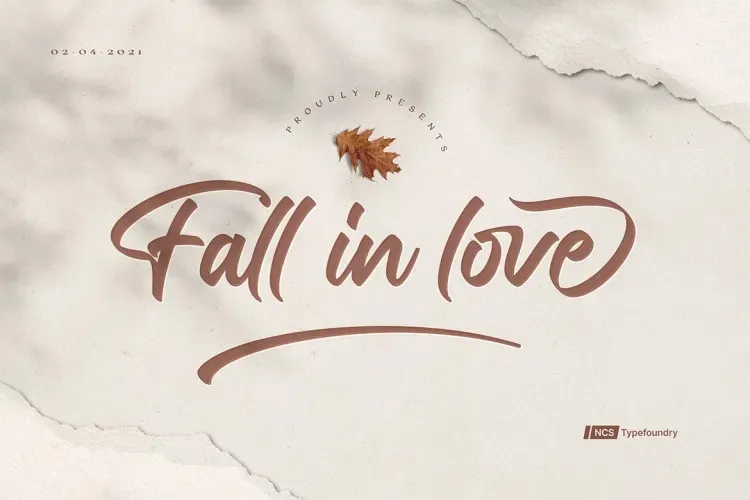
Fall in love Script Font – Download Grátis
A fonte “Fall in Love Script Font” é uma elegante tipografia feita para quem busca um toque delicado e criativo na hora de criar trabalhos artísticos e conceituais. Inspirada no estilo dos traços suaves de desenho a mão, esta fonte foi projetada com detalhes robustos em suas linhas e bordas arredondadas levemente onduladas. Perfeita para aplicar em logotipos, roupas personalizadas, embalagens de produtos e até mesmo assinaturas de estilo estiloso, esta fonte combina harmoniosamente com marcas empresariais e campanhas promocionais. A “Fall in Love Script Font” é uma excelente adição para qualquer projeto que deseja dar um toque delicado e único. Seu design distintivo e de longo alcance torna-a ideal tanto para projetos pessoais quanto para trabalhos corporativos, seja em letras grandes para ambientes publicitários ou pequenos detalhes nos produtos finais. Engane-se se acha que esta fonte é apenas para uso pessoal, ela tem um poder inegável de transformar simples ideias em obras de arte vivas e impactantes. Experimente-a hoje e veja como sua criatividade ganha vida!